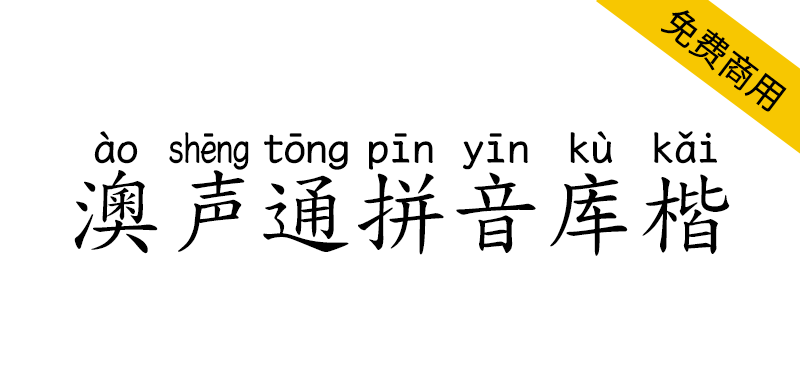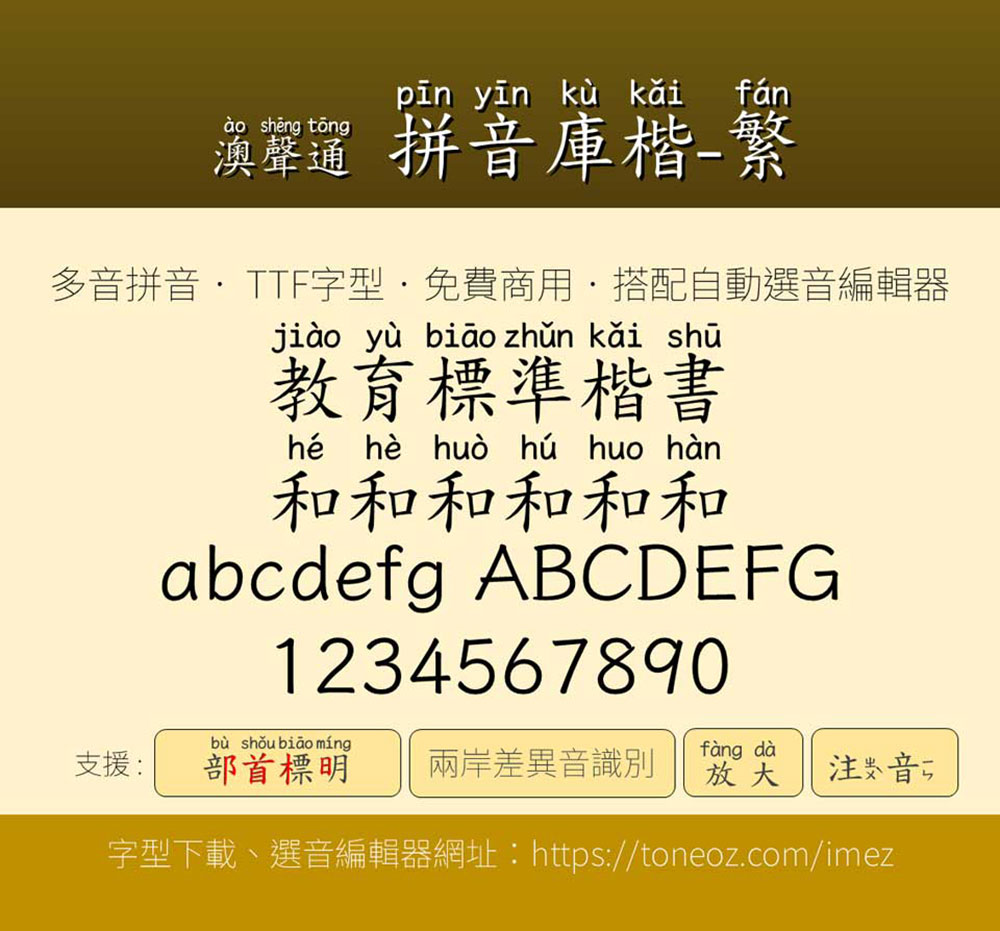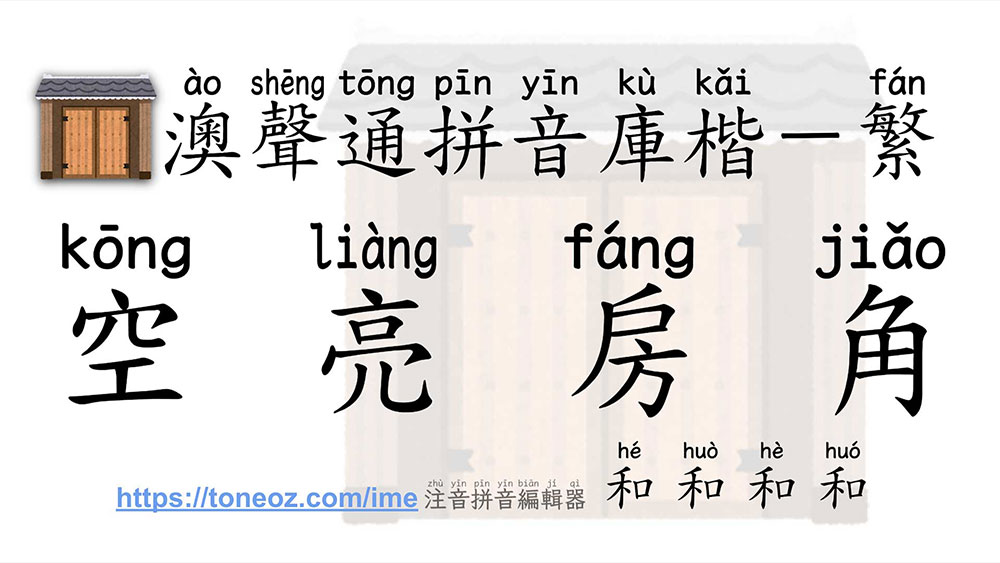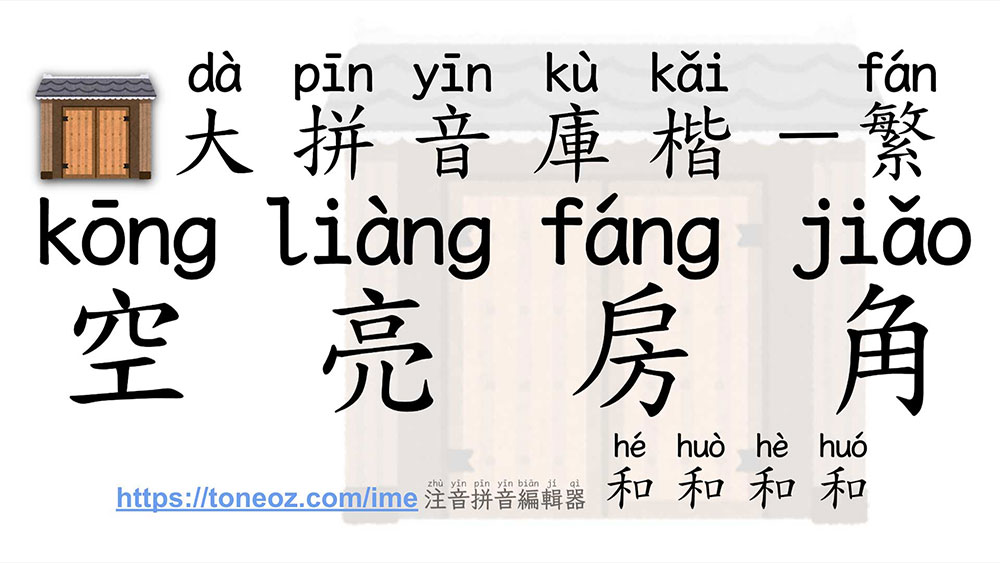
澳声通拼音库楷是一款基于全字库正楷体的可选多音字的TrueType楷体拼音字型,满足中文现场教学需求,搭配国际标准《ISO 7098中文罗马字母拼写法》的汉语拼音字型,适合熟悉罗马字母的学习人士。
标准版(小拼音版)的大小适当不影响字距,适合文章阅读或试卷,大拼音版本适合投影片或标题。每个字的拼音宽度不同,最短的只有一个字母,最长的字「装zhuāng」有6个字母,大拼音字型的拼音此时可能会重叠,使用者可利用字距或者加入空白来调整。